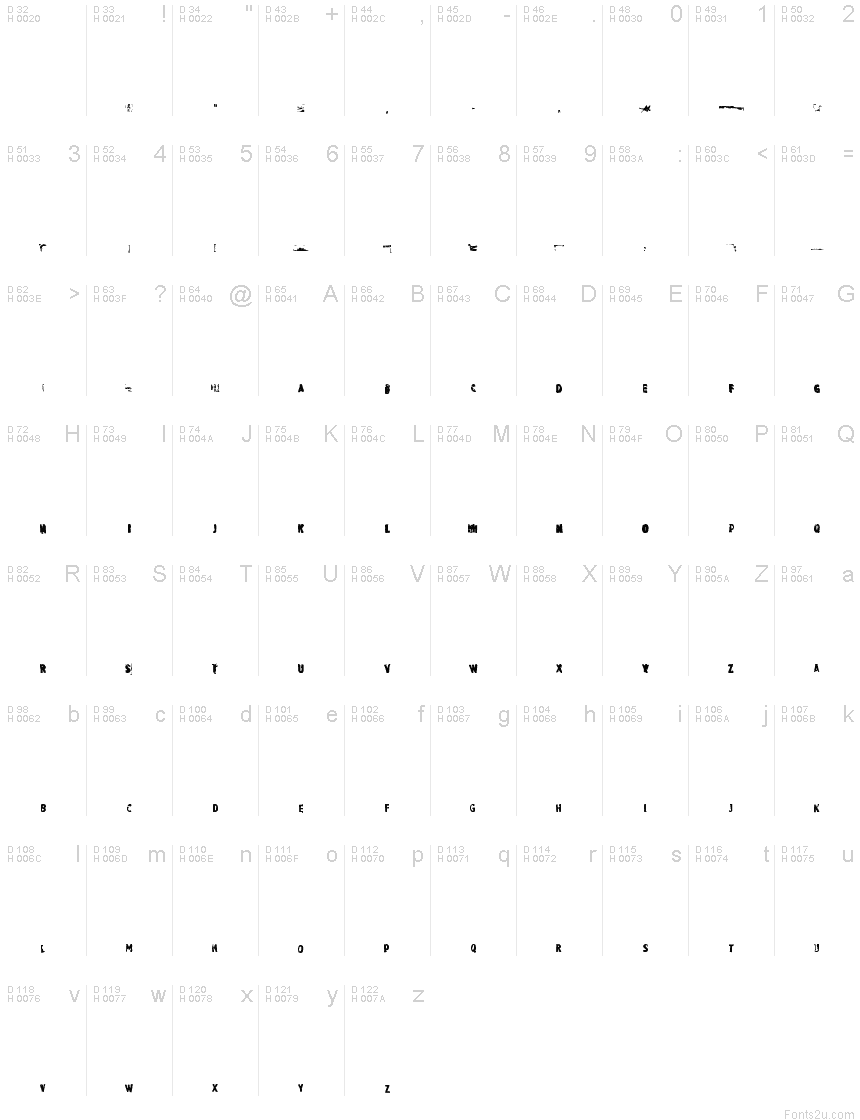
Rubbermaid Single di Dirk Uhlenbrock è un font display gratuito ed eroso, che richiama l'aspetto ruvido di un timbro di gomma. Le lettere appaiono spesse, smussate e fortemente consumate, con bordi scheggiati e incisioni irregolari che danno all'alfabeto un aspetto inchiostrato, vissuto e quasi artigianale.
Questa texture granulosa rende il font perfetto per fanzine, titoli di poster, copertine di dischi, volantini e packaging che cercano un'estetica vissuta e di strada, anziché una finitura pulita. Funziona egregiamente anche per brevi titoli e monogrammi, poiché le maiuscole mantengono il loro peso solido, mentre la superficie usurata le rende vibranti e crude.